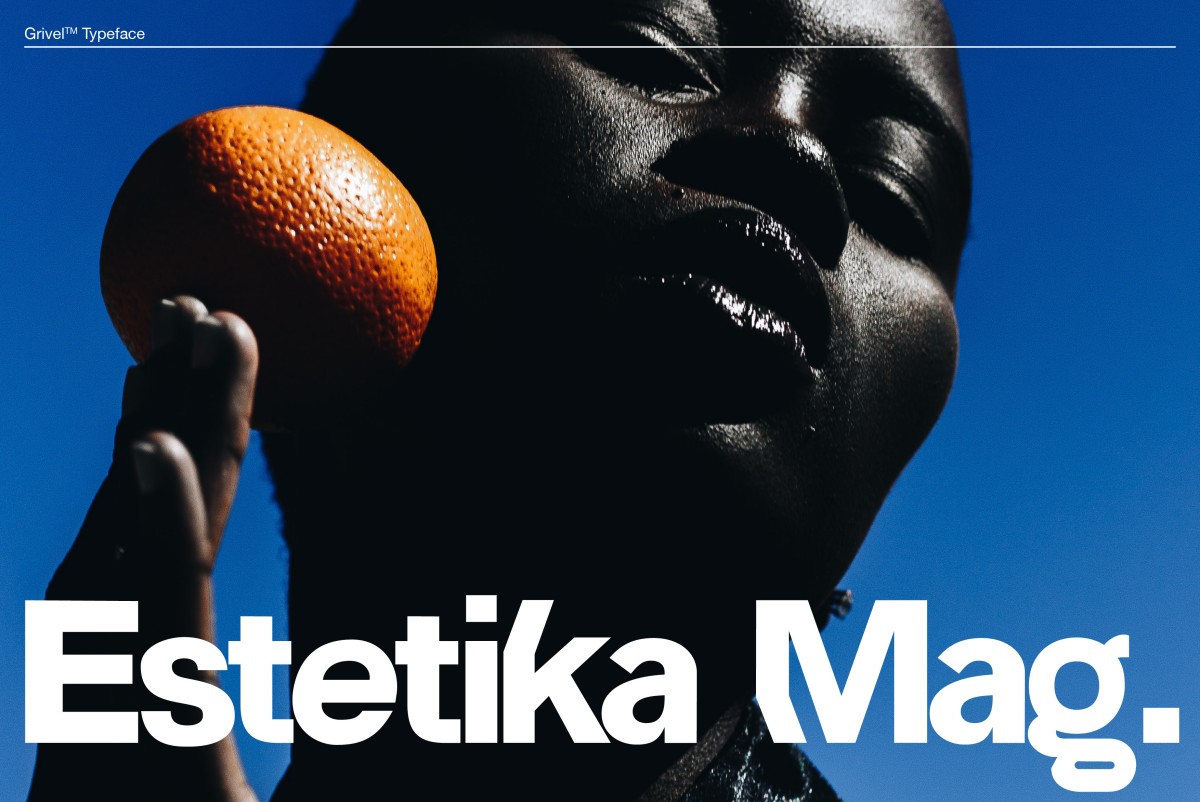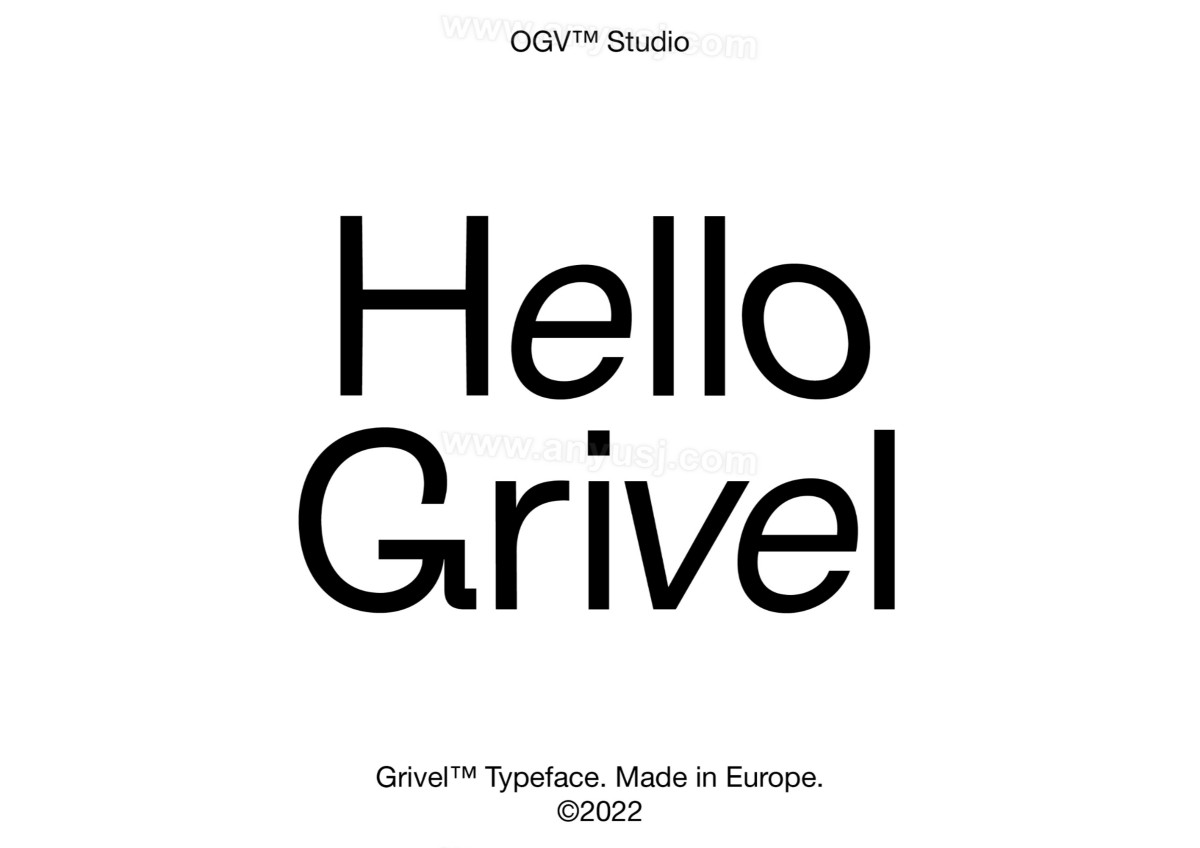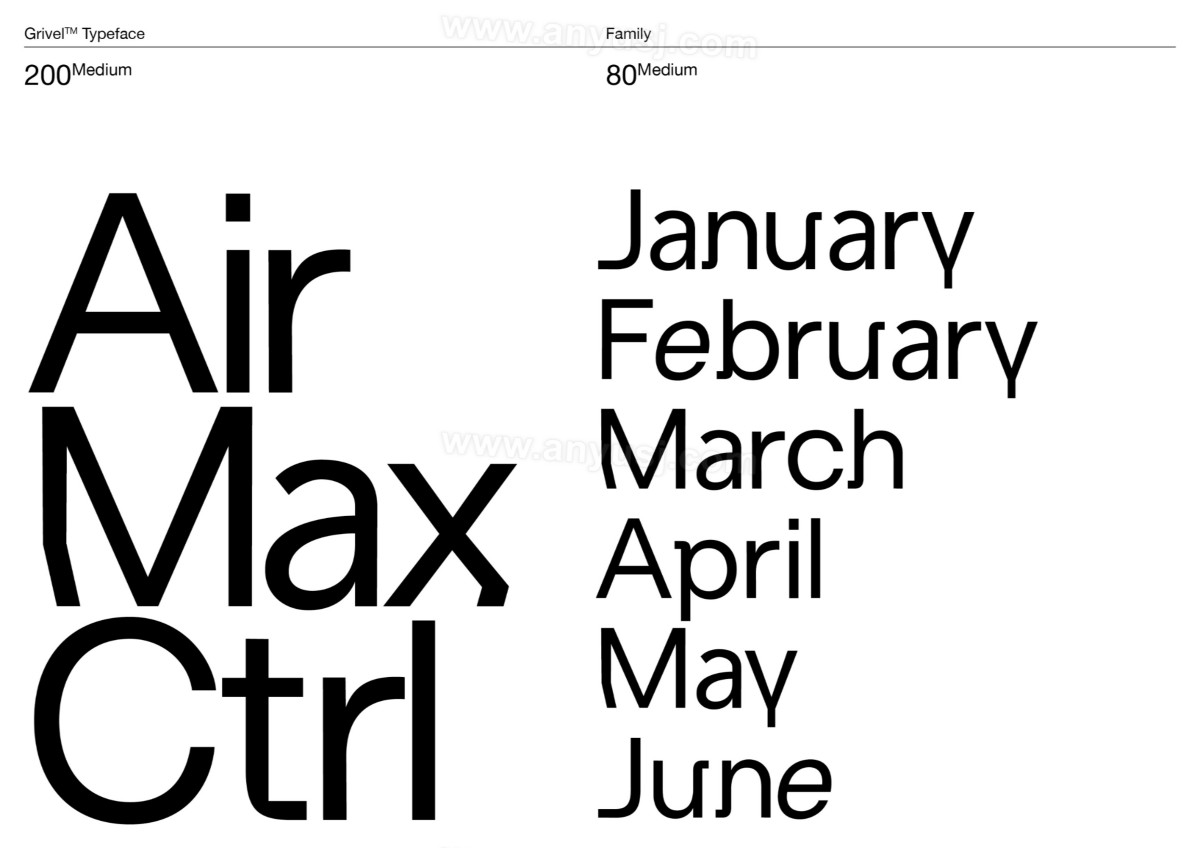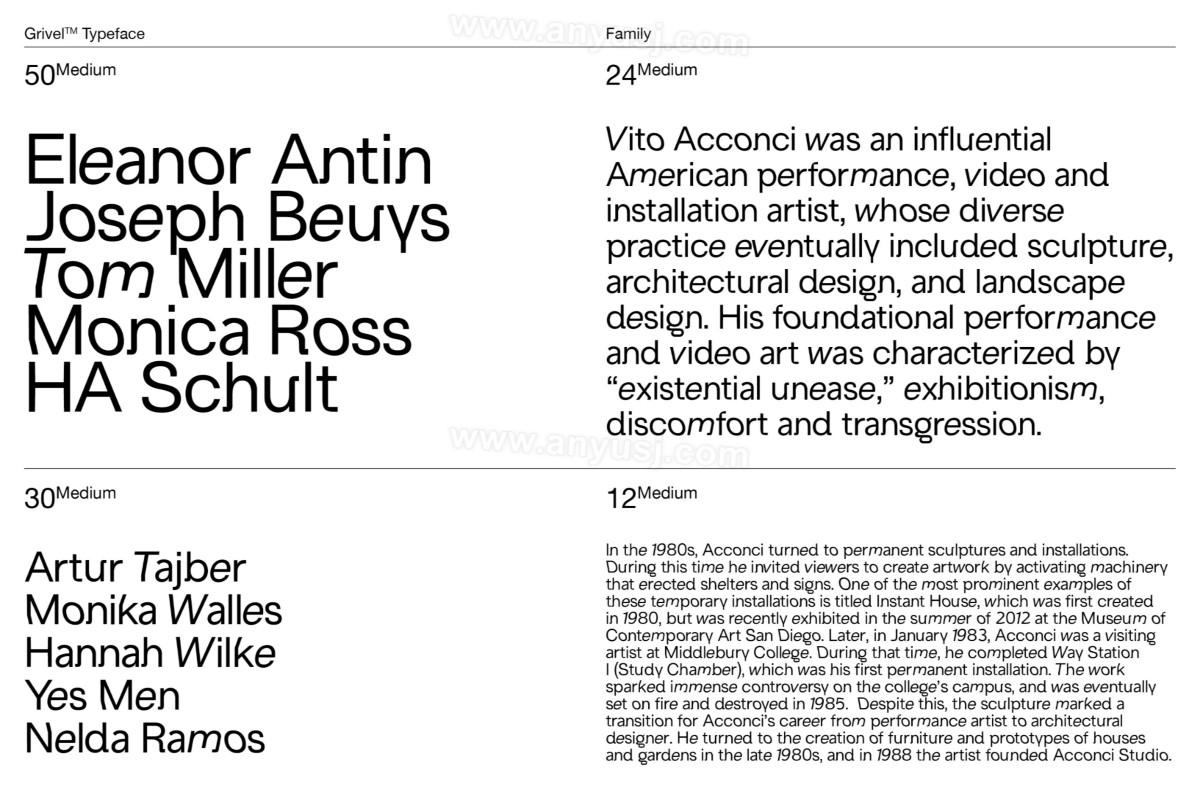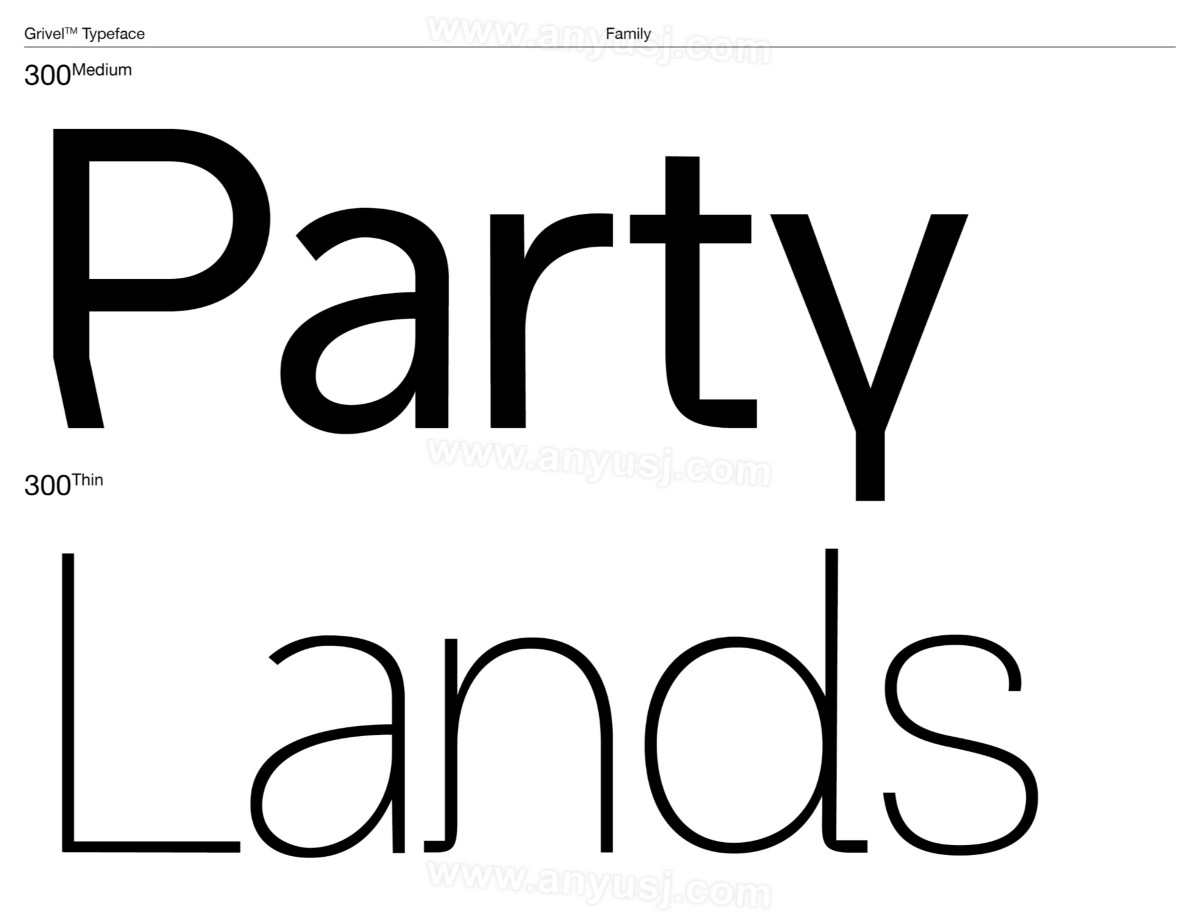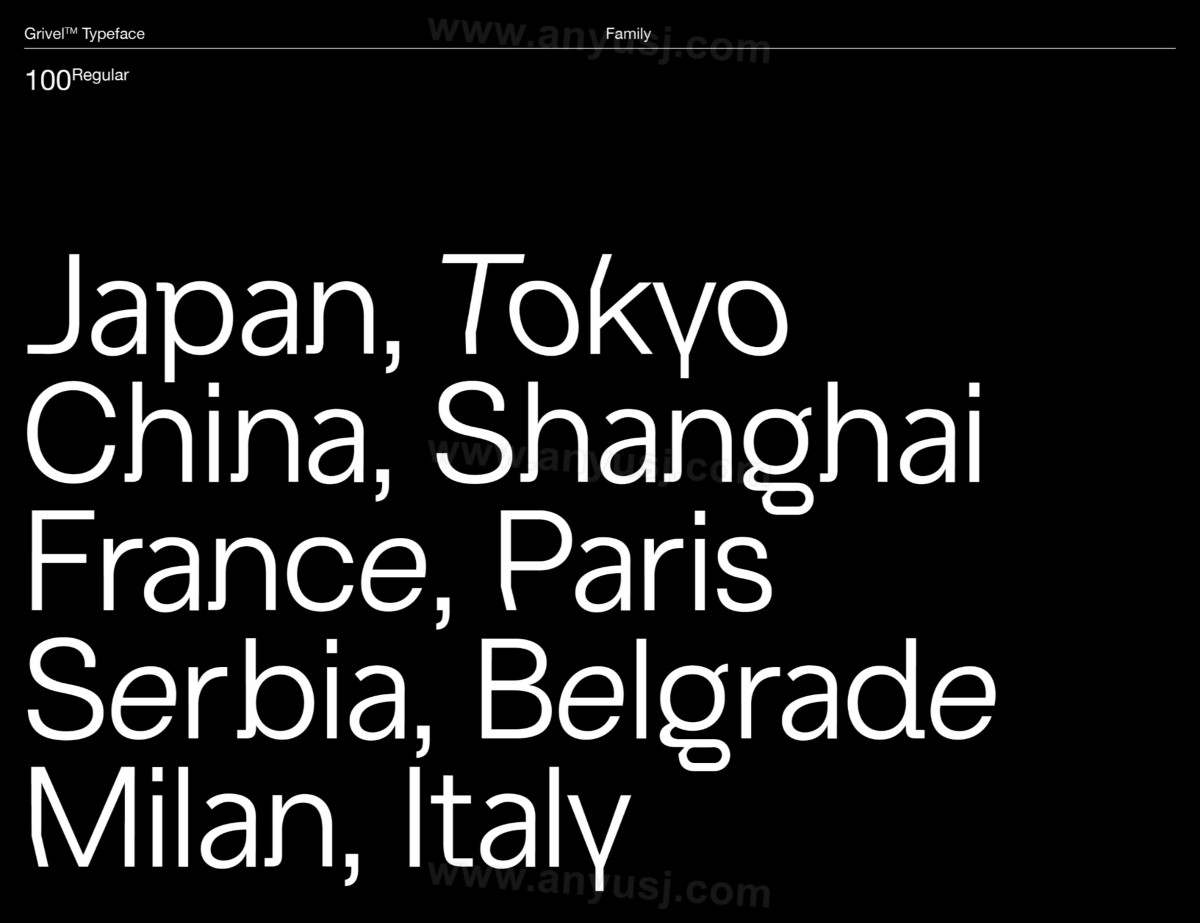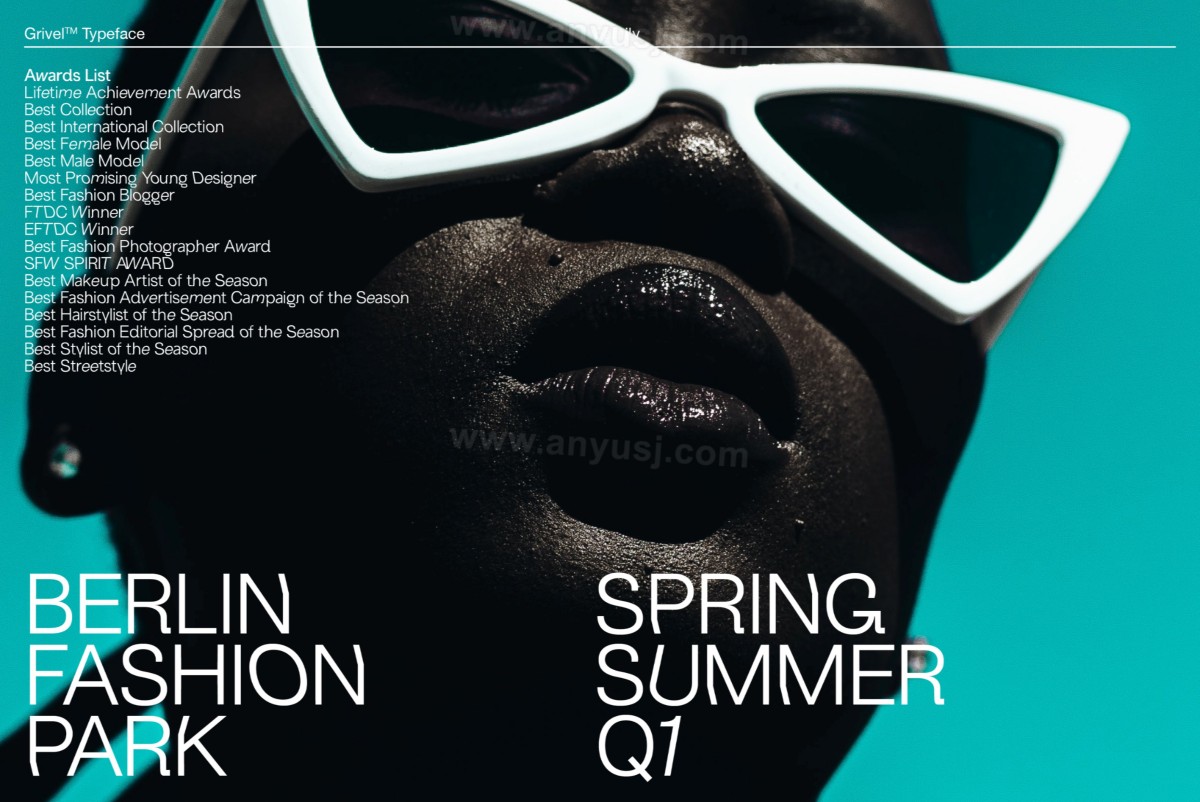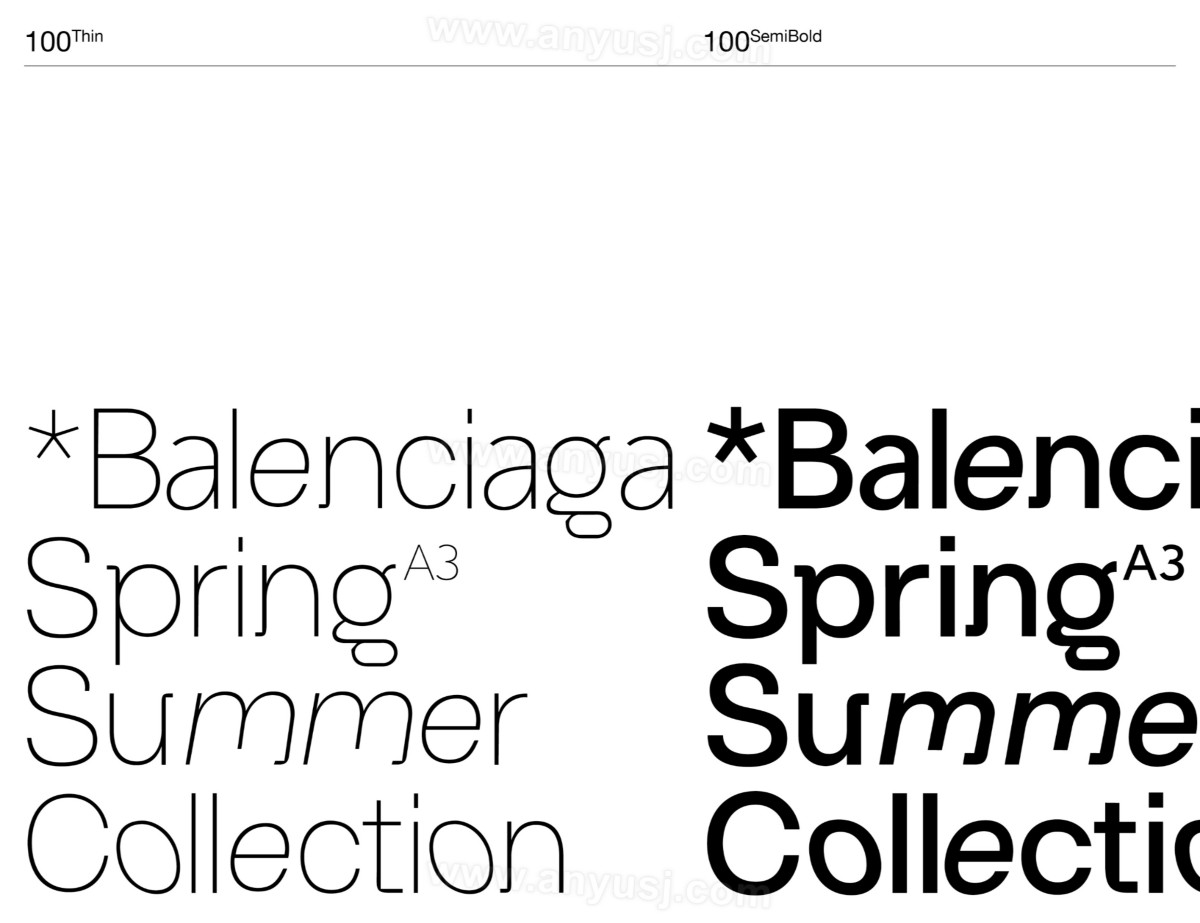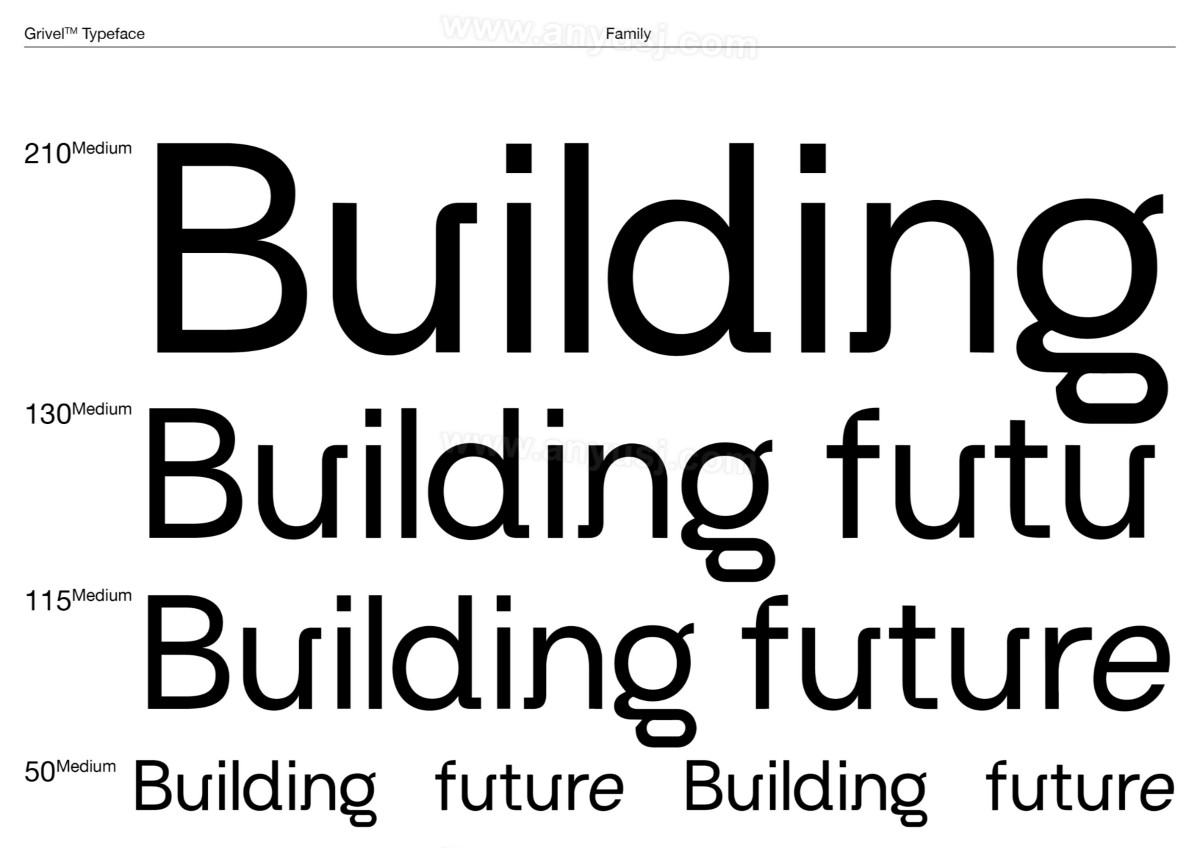
8款干净极简趣味logo标题排版无衬线西文英文字体家族Grivel Typeface
美的空间,同时提供了干净利的审美。优雅的Grivel为实验和演奏提供了完审美之间只有一线之隔。瑞士无衬线字体与奇怪的现代
适用于大小不同的点尺寸。清晰的外观。间隔和掌握最佳可读性。Grivel在各种Grivel充满活力,同时保持干净、项目和应用中表现良好。
一种重量发布,Grivel后来成为八种重量的家族,现它最初于2021年由OGVTM工作室发布。